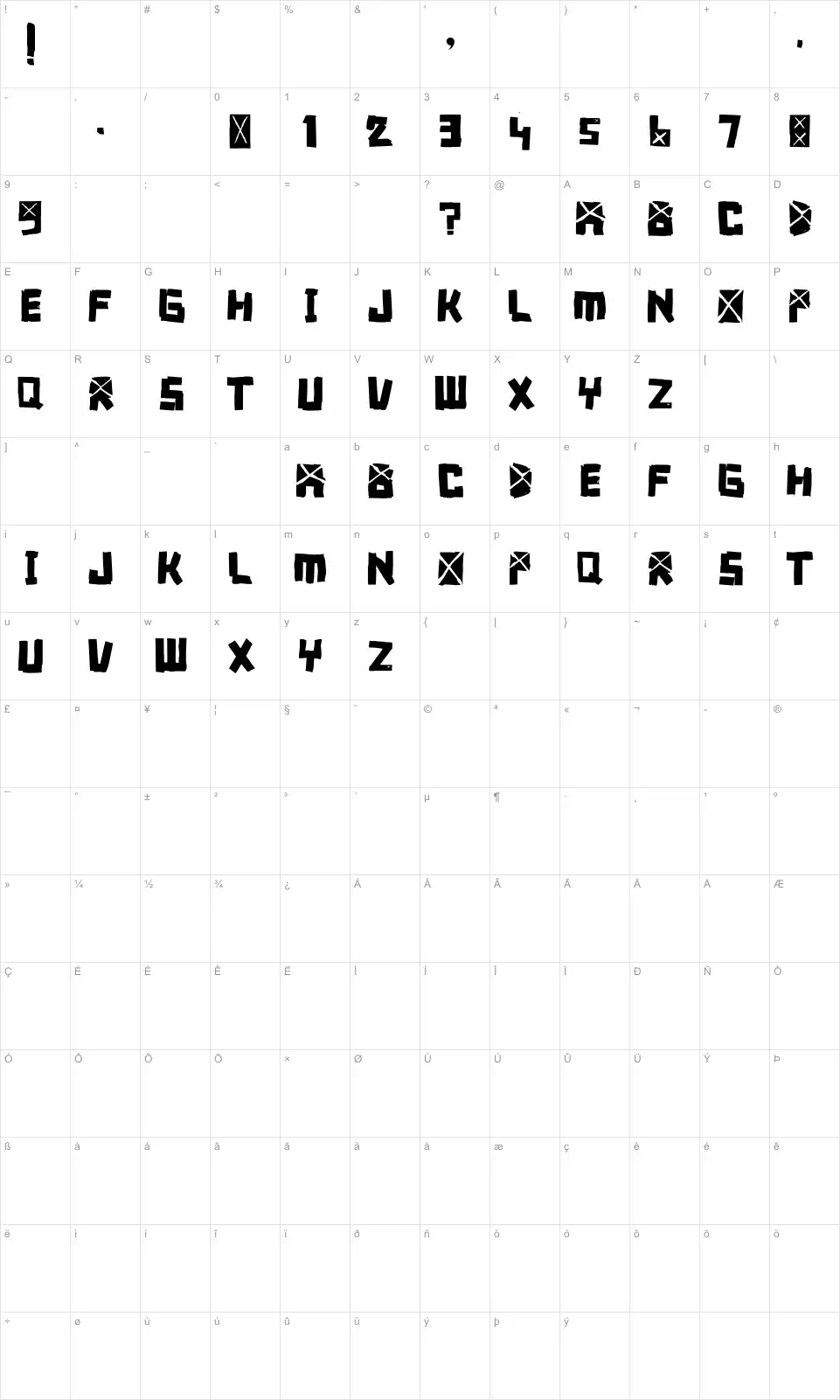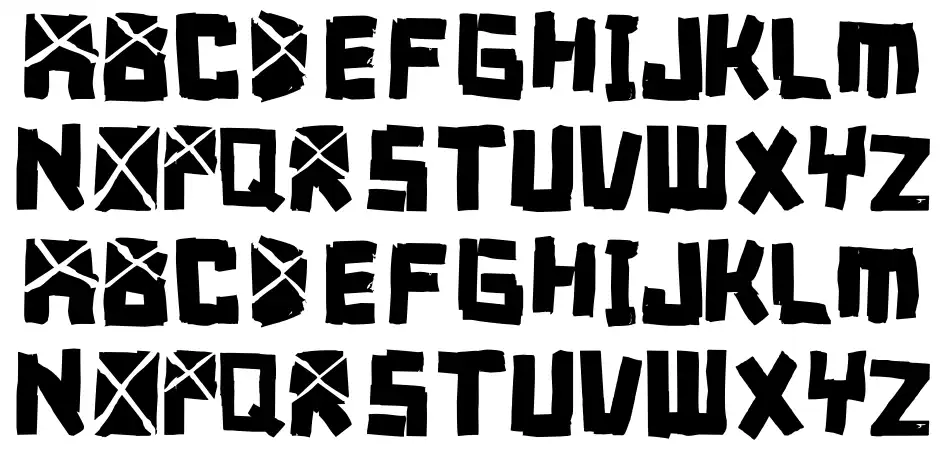
Font Breakdown
A Fonte Breakdown, criada por Nele, é uma fonte Fancy da categoria Stencil And Army. Ela oferece uma aparência chamativa e versátil, ideal para projetos que desejam uma aparição elegante e única. Se você está procurando por essa fonte ou deseja testá-la antes de usá-la, o Font Breakdown font oferece a opção de download ou gerar uma pré-visualização de texto personalizada online. Esta font gratuita está disponível em formato TTF, permitindo-lhe personalizar a aparência de seu design conforme necessário. Adicionada em 11 de julho de 2022, a Font Breakdown está entre as 1826 fontes mais baixadas, demonstrando sua popularidade e qualidade. Com apenas 12 KB, esta fonte é extremamente leve e eficiente, sem comprometer a aparência moderna e elegante que ela oferece.
Designer: Nele